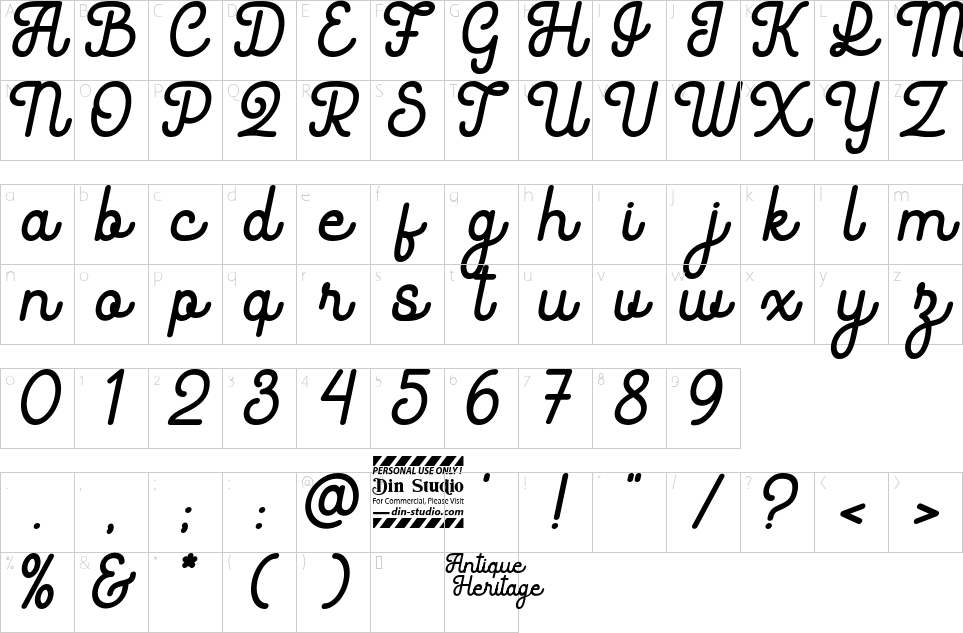
Descubra Antique Heritage, uma elegante e sofisticada fonte que remonta ao passado. Fundamentada na história e no design tradicional, Antique Heritage oferece um toque nostálgico e sofisticado que vai aperfeiçoar qualquer projeto de escrita. Esta fonte foi criada por Donis Miftahudin e tem atraído muitos amantes do design, com seu download de 320 vezes. Não apenas uma fonte de destaque, Antique Heritage é um testemunho do passado, um retrato dos tempos antigos, reunindo elegância e profundidade em cada letra. Descubra por si mesmo o encanto desta fonte única e imbuída de história.